一、英语包装印刷新字体样式
英文字种类关键有白正细体、白正粗字体、白斜细体、白斜粗字体黑正粗字体、黑斜粗字体、花体、题目黑斜体字、题目黑正体、斜黑体字、书版正体、书版斜体字、书版狭身正体、细黑正体、个人名片正黑体字、工艺美术正体、工艺美术广告宣传斜体字、设计装饰体、广告宣传狭身正体等。
二、西文印刷字体
西文本体一般 不一样字型来归类,不一样的造型设计特性,产生了各式各样的字体样式,个性字体集中体现了设计师的个性化,产生了分别的设计风格和特性。在之后的长期性应用中,这种字体样式又派长出很多形变字体样式,这种形变字体样式具备一样的特点和一致的趋向。一般把具备相互特点的字体样式群称之为西文本体管理体系,西文本体多以活字设计师、手工雕刻者、活字锻造者或名人的姓名取名。也有效字体样式的起源地地名大全做为西文本体管理体系的名字。西文本体的类型极其丰富多彩,多种多样,美国有1800多种多样,全球有5000~6000种,西文本体主要是拉丁字母的瑜伽体式。
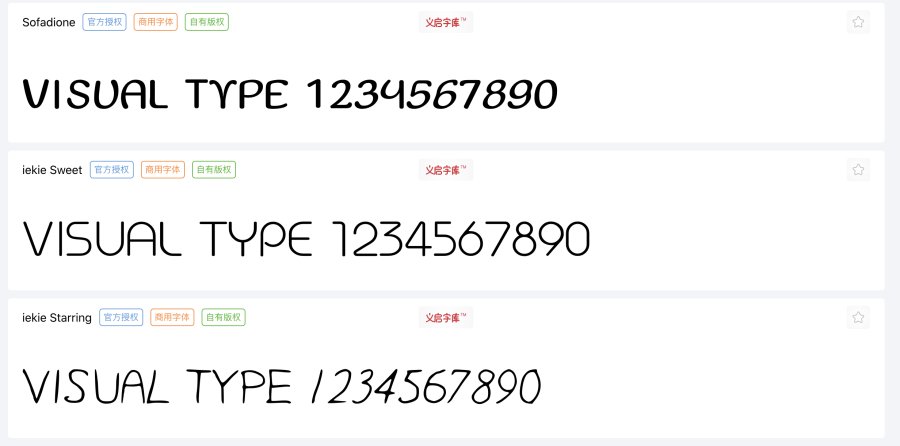
拉丁字母始于绘画,是由古代埃及象形字演化发展趋势而成,希腊人在与腓基尼人到相处中,汲取了她们的文化艺术,造就了希腊字母,变成当代拉丁文字母的原型,到罗马帝国废止前期皇朝政治体制而执行共和阶段,拉丁字母基础定形。古罗马帝国出現时,拉丁字母获得非常大发展趋势并完善起來,拉丁字母的发展趋势不但是一种文化艺术的发展趋势,并且字体样式也向美观大方好用的方位发展趋势。
那时候的腓尼基亚人对先祖的30个标记多方面梳理梳理,合拼为22个简单的型体。之后,腓尼基亚人的22个英文字母传入了爱琴海岸,被希腊人所运用。公元1世纪,罗马帝国推行共和时,更改了平行线形的古希腊字体样式,选用了拉丁人的设计风格轻快、带浮夸环形的23个英文字母。最终,古罗马帝国以便操纵欧州,加强规范字沟通交流方式趋一,也以便融入欧州各中华民族的語言必须,由I派长出J,由V派长出U和W,遂完成了二十六个拉丁字母,产生了详细的拉丁文字系统软件。
罗马字母时期最重要的是公年1到2新世纪与古罗马建筑另外造成的在凯旋门、获胜柱和出土文物墓碑上的严肃雅致、均匀美观大方和彻底成熟了的罗马帝国英文大写体。文艺复兴时期阶段的艺术大师们夸赞它是理想化的古典风格方式,并把它做为学习培训古典风格英文大写字母的范体。它的特点是字脚的形状与纪念柱的柱子类似,与立柱十分和睦,英文字母的宽度占比适度美观大方,组成了罗马帝国英文大写体极致的总体。
在初期的拉丁字母管理体系中并沒有小写字母,公年4新世纪--7新世纪的安塞尔字体样式和小安塞尔字体样式是小写字母产生的衔接字体样式。公年8新世纪,荷兰卡罗琳皇朝阶段,以便融入顺畅迅速的撰写必须,造成了卡罗琳小写字体,传说故事它是查理一世授权委托美国专家学者凡·约克在荷兰开展文字改革分类整理的。它比以往的文本写的快,又有利于阅读文章,在那时候的欧州广为人知应用。它做为那时候最美观大方好用的字体样式,对欧州的文本发展趋势起了根本性的危害,产生了自身的辉煌时代。
15世纪是欧洲文化发展趋势极其重要的阶段,在这里一时期意大利人古腾堡创造发明铅活字印刷术,对拉丁字母型体的发展趋势起了极其重要的危害。原先一些连写的英文字母被包装印刷活字解除了,开辟了拉丁字母的新设计风格。另外这一时期更是欧州文艺复兴时期阶段,技术性与文化艺术的发展趋势、兴盛快速促进了拉丁字母管理体系的发展趋势与健全,广为流传出来的罗马帝国英文大写字体样式和卡罗琳小写字体根据西班牙等我国的改动设计方案,极致地结合在一起。卡罗琳小写字体历经持续的改善,这时候获得了宽和圆的型体,它开朗的线框与罗马帝国英文大写字体样式娴雅的型体中间的分歧获得了圆满的统一。这一时期是字体样式设计风格造就更为繁荣昌盛的阶段。
18世纪法国大革命和启蒙运动之后,新起官僚资本主义倡导古希腊古典艺术和文艺复兴时期造型艺术,造成了现代主义的风格特征。整齐挺直的线框替代了圆弧状的字脚,荷兰的这类审美观点危害了全部欧州。荷兰最知名的字体样式是迪多(FirminDidot)的同名的字体样式,更为注重大小线框的明显比照、质朴、冷严但又无失聪明伶俐和蔼。迪多的这类风格特征合乎了法国大革命的精神实质,是有实际意义的。在西班牙,具有“包装印刷者之首”和“神之包装印刷者”头衔的波多尼(GiambattistaBodoni)的同名的字体样式和迪多一样有明显的大小线框比照,但在可读性与和睦上做到了高些的功底,因而今日仍被世界各国高度重视和普遍的运用着。它和加拉蒙、卡思龙全是归属于拉丁字母中最知名的字体样式。
二十世纪八十年代至今,计算机技术逐步完善,在设计方案行业逐渐变成关键的主要表现与制做专用工具。在这个情况下,文字设计出現了很多新的表达形式。运用电脑上的各种各样图像处理作用,将字体样式的边沿、肌理效果开展诸多解决,使之造成一些全新升级的视觉冲击。最终是应用各种各样方式,将字体样式开展组成,使字体样式在图形界面层面踏入了新的方式。
拉丁字母的归类:
拉丁文的字体种类许多 ,一般 大家依据字体样式的发展趋势和特性归类。拉丁字母字体样式一般按管理体系分,每一管理体系中又有很多瑜伽体式。管理体系分成罗马体管理体系、哥特体管理体系、印度体管理体系、无饰整线管理体系、手写体管理体系、装饰设计体管理体系、图型体管理体系。每个管理体系里分别又有一些字体样式。
Windows字体分成光纤传感器字体样式(.FON)和可放缩字体样式;也可分显示屏字体样式、复印字体样式及其复印和显示屏都可用的字体样式。TrueType字体样式(TTF)便是复印和显示屏都可用的可放缩字体样式。也有一种字体分类方式:占比字体样式和固定不动字体样式,即英文字和字体样式。
有一类字体样式是大家很感兴趣的,它应用的字符集与WindowsANSI或OEM字符集没什么相同之处,大家称之为非文章正文字体样式或符号字体。最重要的是“Marlett”。它是Windows的系统字体之一,菜单栏中的“4”,对话框右端利润最大化、降到最低、复原、关闭按钮,单项选择题、勾选框前的“√”,及其用以情况条中的“56”这些,全是用该字体样式创建的。此字体样式不可以删掉,不然上述情况标记都将变成数据方式。
此外,用得较多的字体样式有:“Symbol”、“Wingdings”、“Webdings”、“MonotypeSorts”和“MTExtra”(后二种为office97所需)。在其中“Symbol”字体样式用以公式中,包含希腊字母、数据、运算符、集合符号和其他标记;“Webdings”字体样式汇聚了生活起居中常见的表意文字标记,如:电話、书籍、近视眼镜、信封袋、剪子、时钟、手式、箭头符号等;“MonotypeSorts”中包括了200多种多样箭头符号、标示符和标识;“MTExtra”中仅有非常少的数学符号,用于扩大“Symbol”字体样式。“Webdings”字体样式是对“Marlett”和“Wingdings”字体样式的填补。
电子计算机中字型库分成低分辨率和高像素两类:
低分辨率字型库用以一般的数据分析系统。又分成三个级别,低挡筒易(16X16点阵式)、中等普及性(24X24点阵)、高端提升型(32X32点阵式)。高像素中国汉字字型库关键用以包装印刷系统软件。用以包装印刷系统软件的字型库务必在64X64点阵式之上,而激光照排系统软件高精密中文字库则必须100X100之上的点阵式字型。
点阵式方法
点阵式字型是一种文本在电子计算机中文字库中字型信息内容的储存方法,这类方法称之为点阵式智能化。文本不管怎样转变都能够写在一样尺寸的格子内,即把一个格子分为256个小方格,或有256个“点”。点阵式中每一个点就有一种情况,即有笔画和无笔画。有笔画的就可以勾勒文本的字型,因此 称之为点阵式字型。若用二进制数据来表明点阵式,1表有笔画,0表无笔画,点阵式字型就需要能用一连串的二进制数据来表明,这类方式称之为点阵式智能化。点阵式的等级越多,文本的数据量越大,字型表明越精准。
特性:低规范点阵字的特性是能应用单纯性字,字型不整齐,有显著的台阶,欠缺艺术美。等级越多,字的精密度就高才可以反映出字体样式的设计风格。可是这类点阵式的字体样式若要用以包装印刷,字体样式的数据量非常大,不方便,并且实际效果还比不上别的方式的中文字库。
这类关键用以电子计算机的显示信息和输出打印。
精密型中文字库
也称智能化中文字库。一般是由200X200、400X400之上的点阵式构成,能用以照排和包装印刷。近些年,国际性上时兴的PostScript网页页面描述语言发展趋势迅速,这类語言把字型当做图型,把文本做为图像处理,进而使字型转变十分丰富多彩,更为美观大方。特性是字型美观大方,边沿光洁,字的笔画伸展当然,能极致重现字体样式的设计风格。
但伴随着包装印刷精密度的提升,这类中文字库也不可以非常好的考虑包装印刷规定了。
矢量字库
高精密中文字库仅仅对于300DPI上下的輸出,出現1000